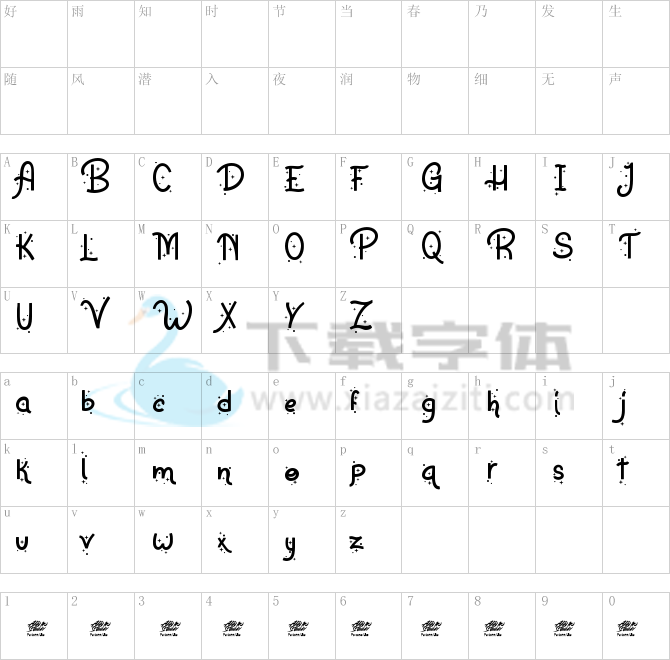
Anigira Display.ttf字体下载,这款字体结构工整、笔画清晰,兼顾美观与易读性,适用于标题、正文、海报、包装、LOGO 等多种场景。字形优雅稳定,风格百搭耐看,适配日常排版与创意设计,让文字呈现更舒适、更具质感。Anigira Display.ttf字体下载一笔一画,皆是细节,以均衡的比例、流畅的线条打造舒适视觉体验,字形端正大气,风格简约现代。无论是商业设计、品牌宣传还是日常排版,都能轻松驾驭,让文字更有格调与力量。Anigira Display.ttf字体下载字体下载。